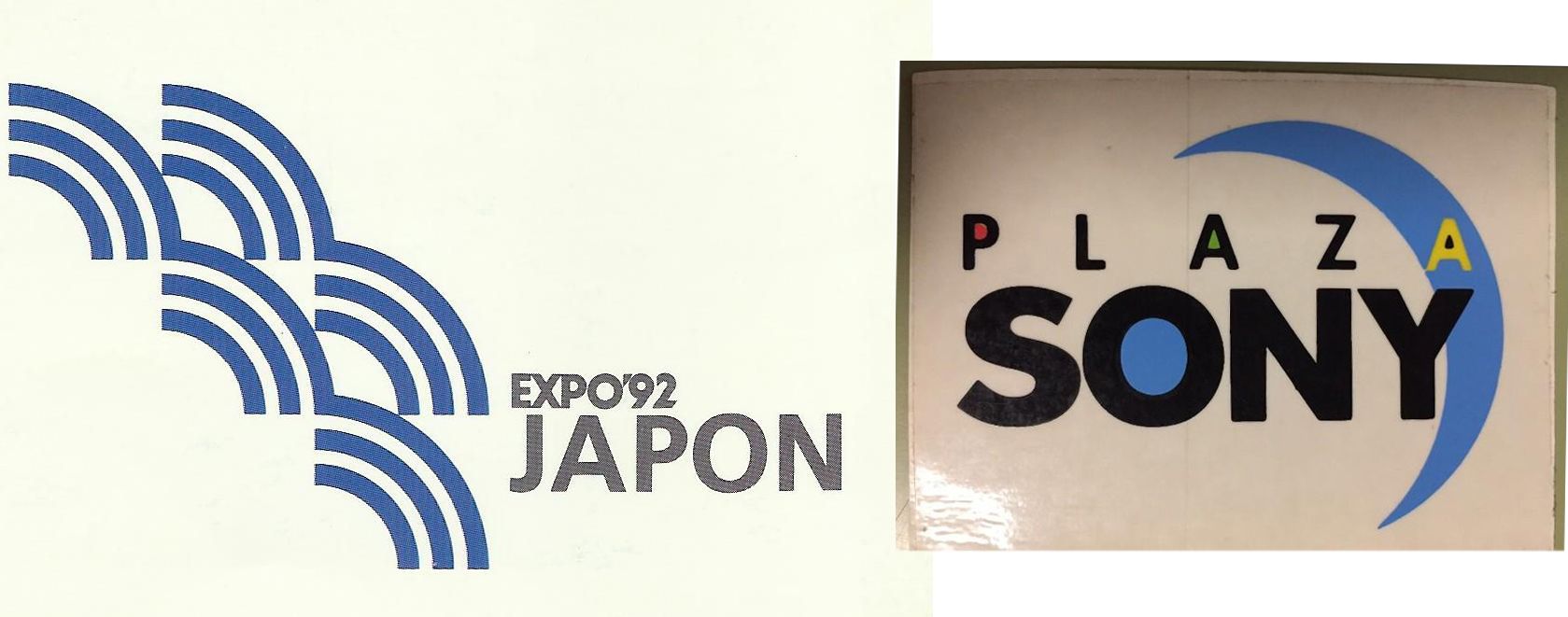
¿alguna web para identificar tipos antiguas?
Hola, estoy intentando identificar fuentes que he encontrado en algunas bolsas de comercios de mi ciudad antiguas. Mi suposición a priori es que antes no habría tantas tipografías y menos en mi ciudad, que es pequeña, por tanto no debería tener problemas, pero no hay manera. Intento identificarlas mediante webs de reconocimiento de tipografía, pero me salen algunas que no tienen nada que ver ni morfológicamente ni en cuanto a denominación, pensaba que me sonaría alguna, pero nada.
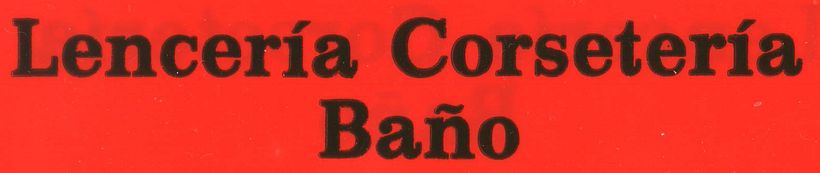
En este ejemplo no creo que sea una fuente muy rara, pues nada, no la puedo identificar. También he estado probando con algunos logos antiguos, que no tienen tipografías complejas.
El resultado es el mismo. Nulo. En algún caso he podido intuir que había una Helvetica Neue LT pero los identificadores me indicaban nombres súper raros de sucedáneos y encima de pago. Necesito saber si hay alguna web que identifique las típicas fuentes Arial, Helvetica, Courier, Swiss, Century Gothic...